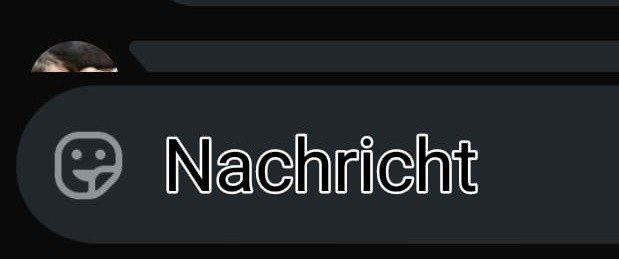
Ingolf22 Fortgeschrittenes Mitglied 29 #1 Habe plötzlich diesen "hohlen" Schriftstiel, weiß aber nicht ob ich das selber verstellt habe. Wie ändere ich das ?
Habe plötzlich diesen "hohlen" Schriftstiel, weiß aber nicht ob ich das selber verstellt habe. Wie ändere ich das ?
bhf Enthusiast 1.835 #2 Einstellungen - Anzeige - Schriftgröße und -stil - Schriftstil Dort die gewünschte Schriftart auswählen. Wobei standardmäßig nur 4 Schriftarten installiert sind, keine davon ist hohl wie abgebildet.
Einstellungen - Anzeige - Schriftgröße und -stil - Schriftstil Dort die gewünschte Schriftart auswählen. Wobei standardmäßig nur 4 Schriftarten installiert sind, keine davon ist hohl wie abgebildet.